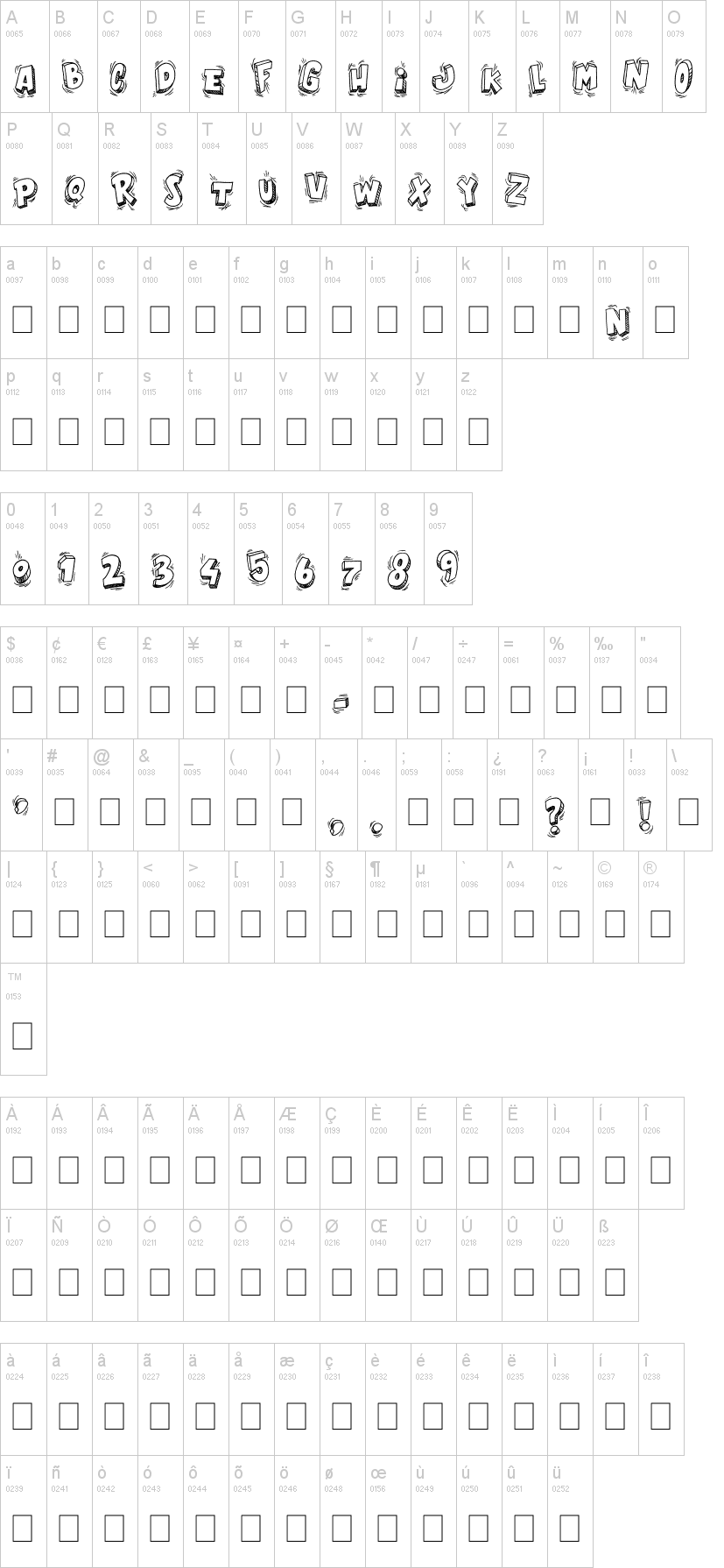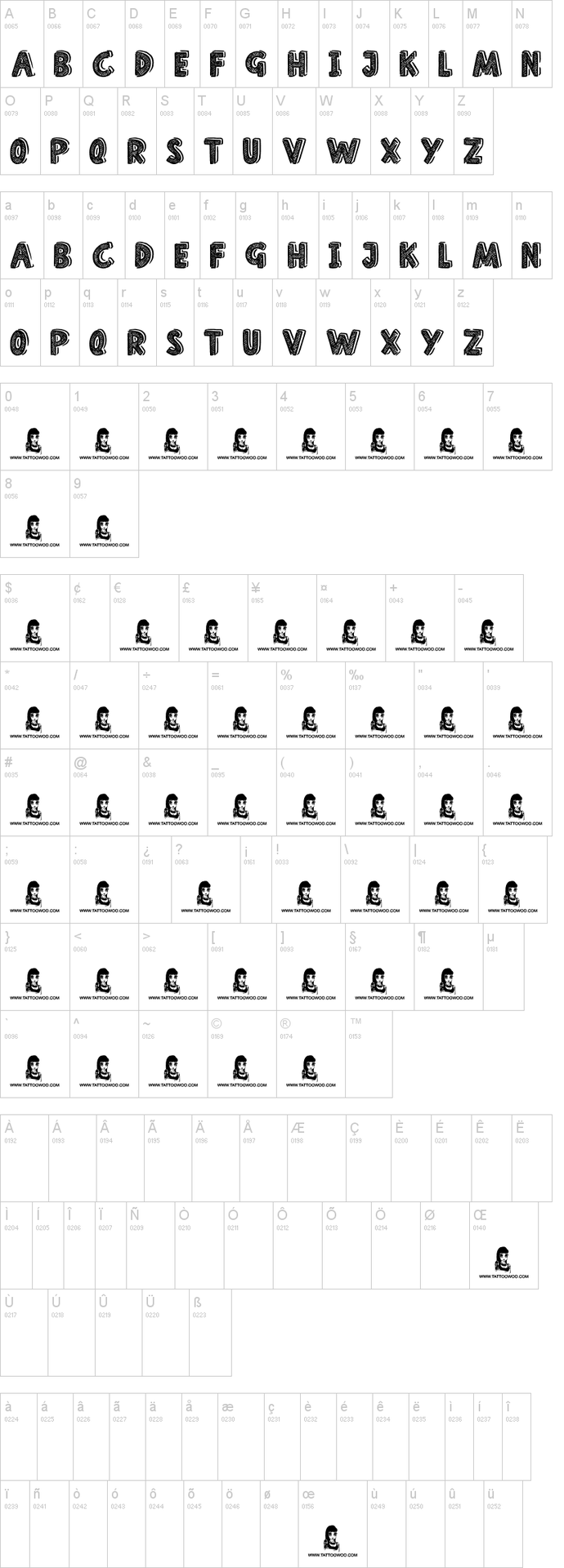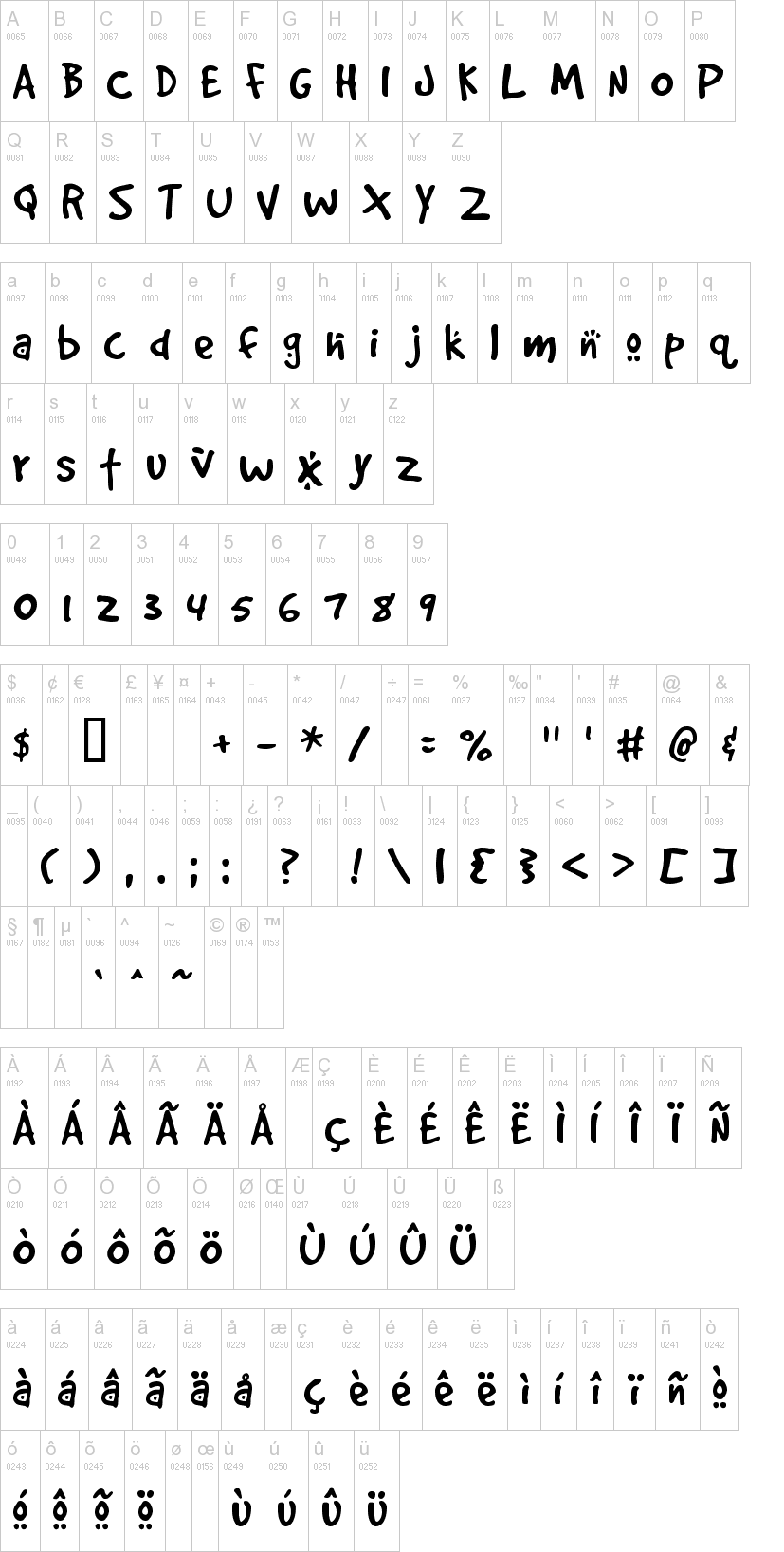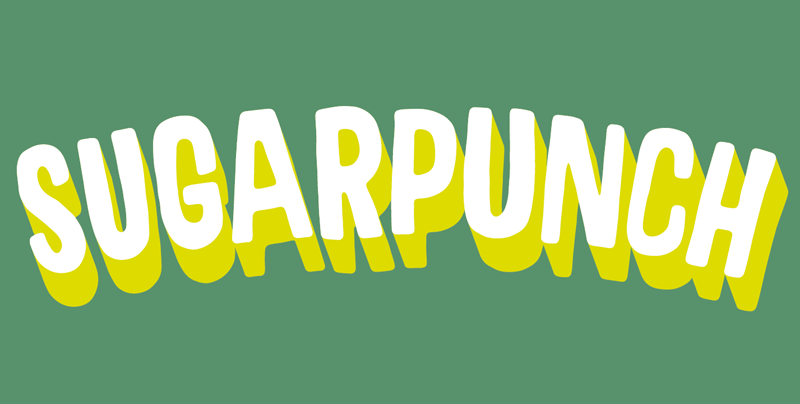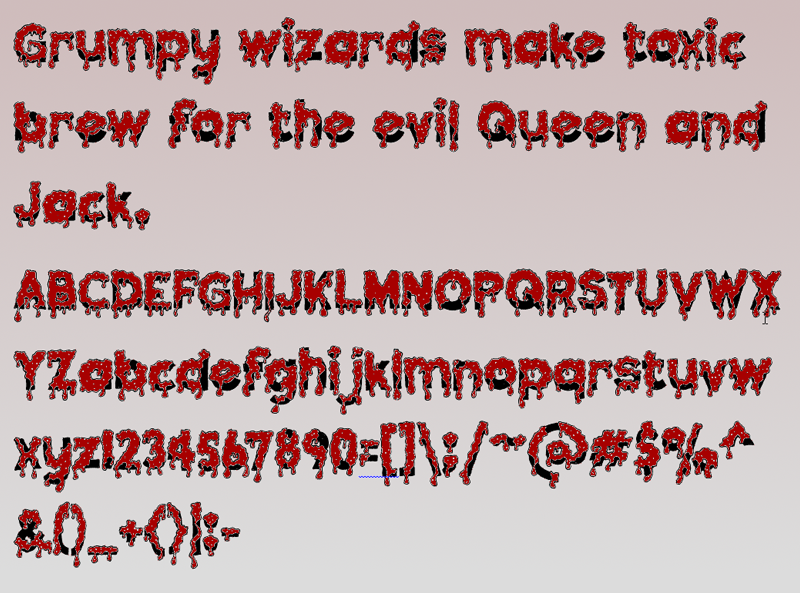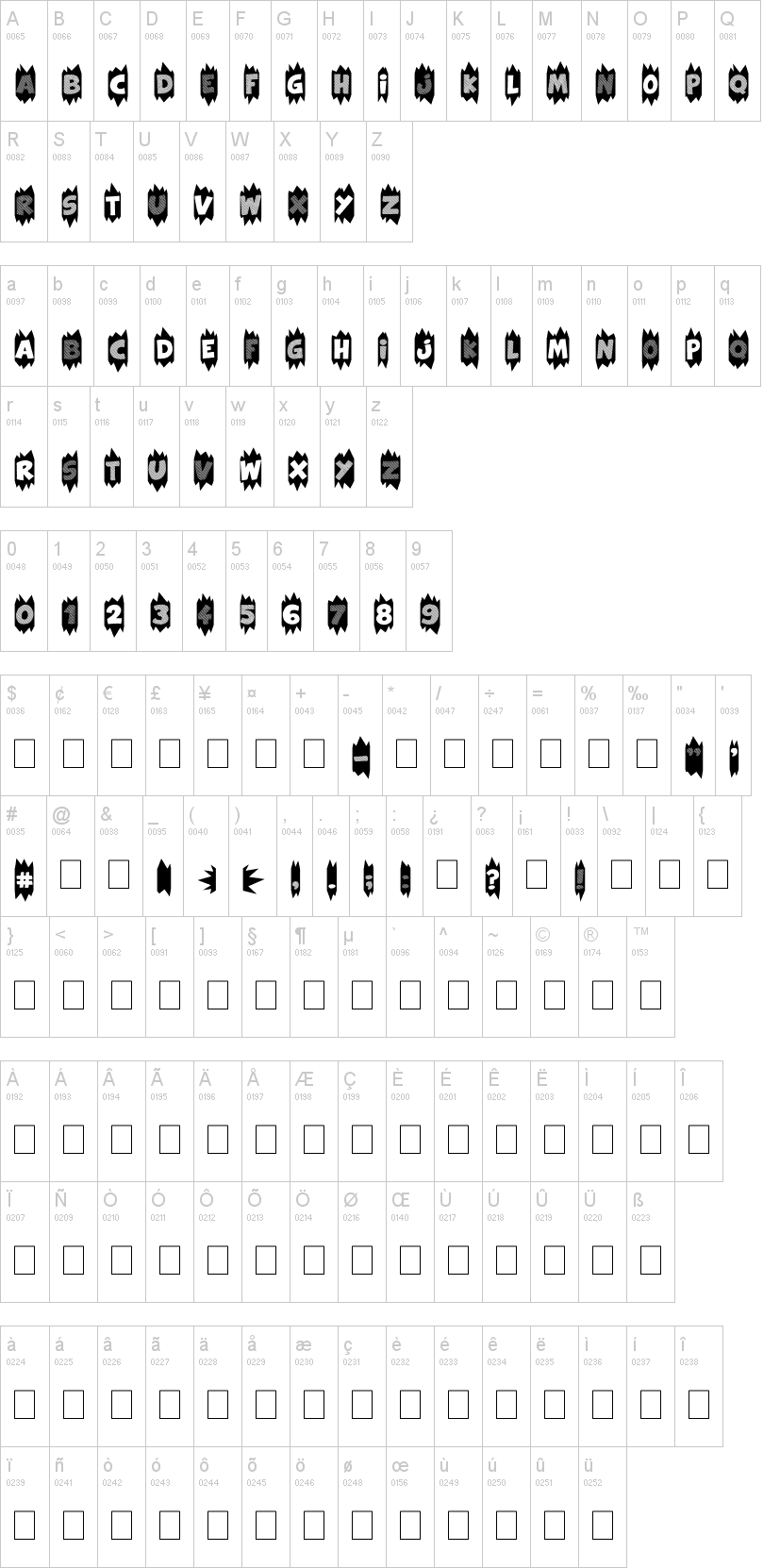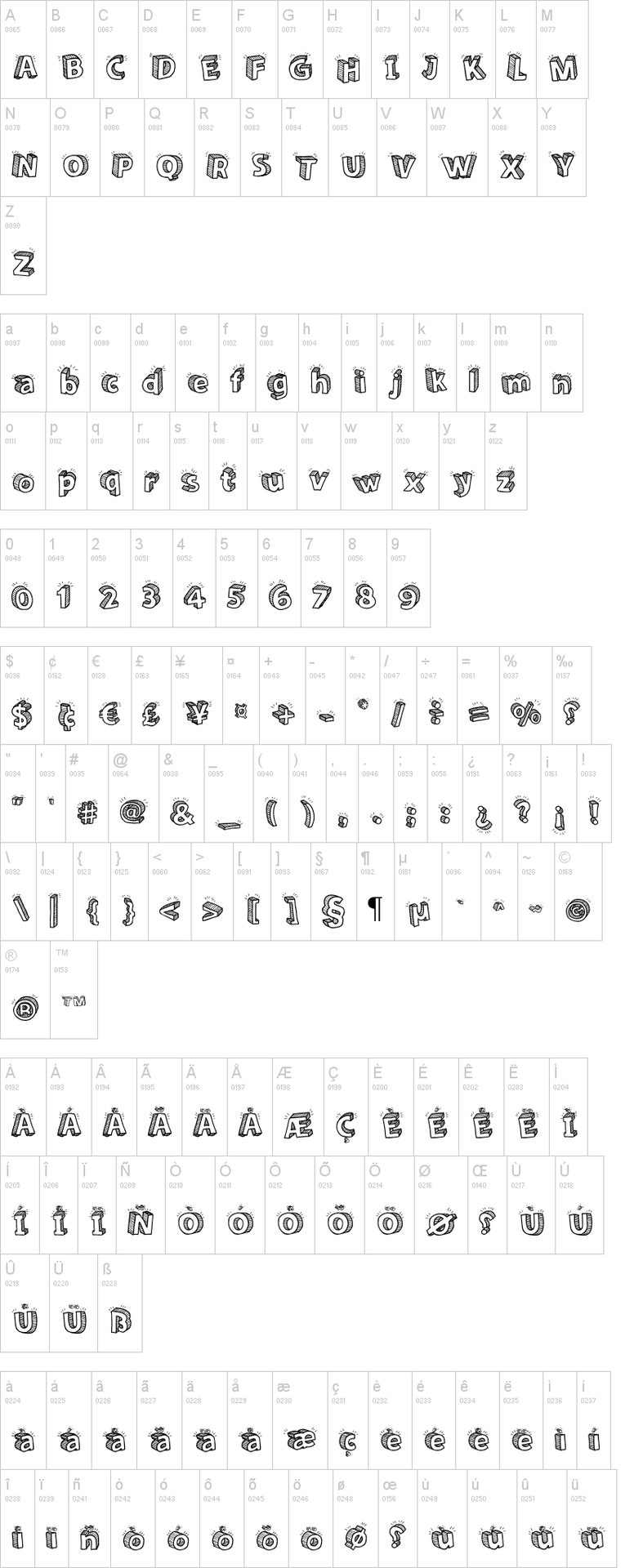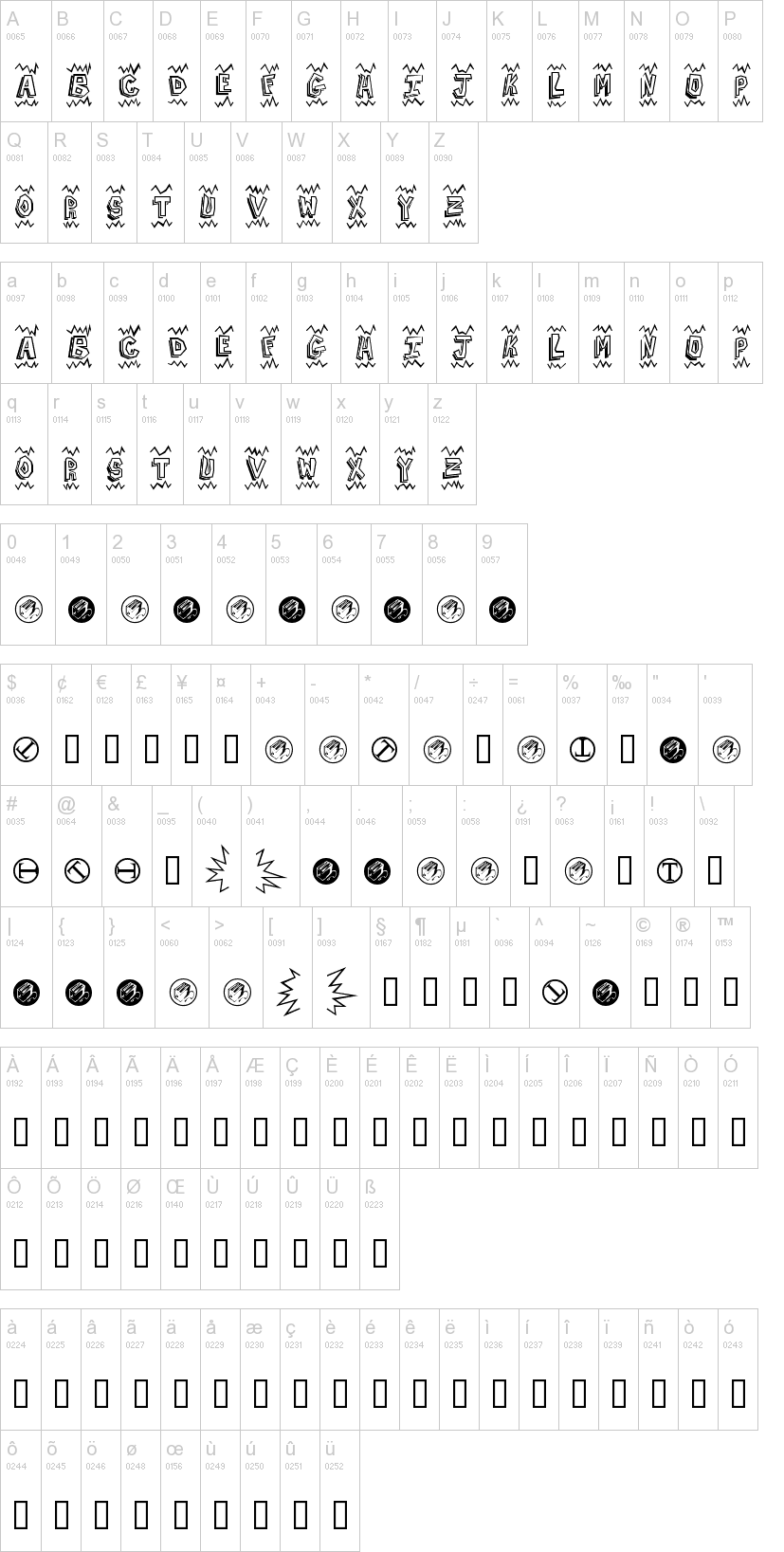
/ CARTOON FONTS /
I , Good Morning
II, Pokemon
III, Orange Juice
IV, Sketch 3D
V, Good dog
VI, Caricature
VII, Supersonic Rocketship
VIII, Super Mario Bros .
IX , Batman Beat the hell Outta Me
X, Home School
XI, Sugarpunch
XII, Gooey Drippy Sticky
XIII , Gretoon
XIV , Yahoo
XV, Cute Cartoon
XVI , PW Yummy Donuts
XVII , Extra Sales